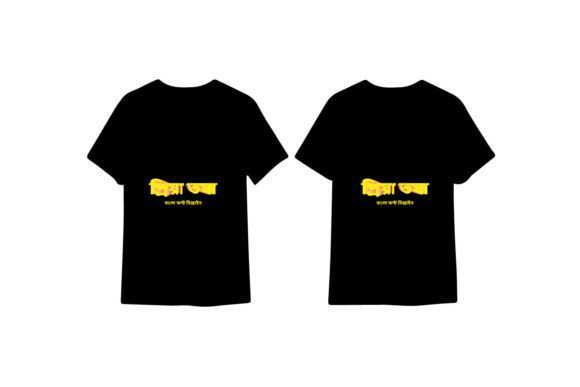
Font Design T Shirt Design
適切なデザイン要素を見つけるのは難しい場合がありますが、Font Design T Shirt Designは作品を即座に引き立てる優れたコレクションを提供します。
POD(オンデマンド印刷)製品、結婚式の招待状、またはソーシャルメディアのグラフィックを作成している場合でも、Font Design T Shirt Designは理想的です。